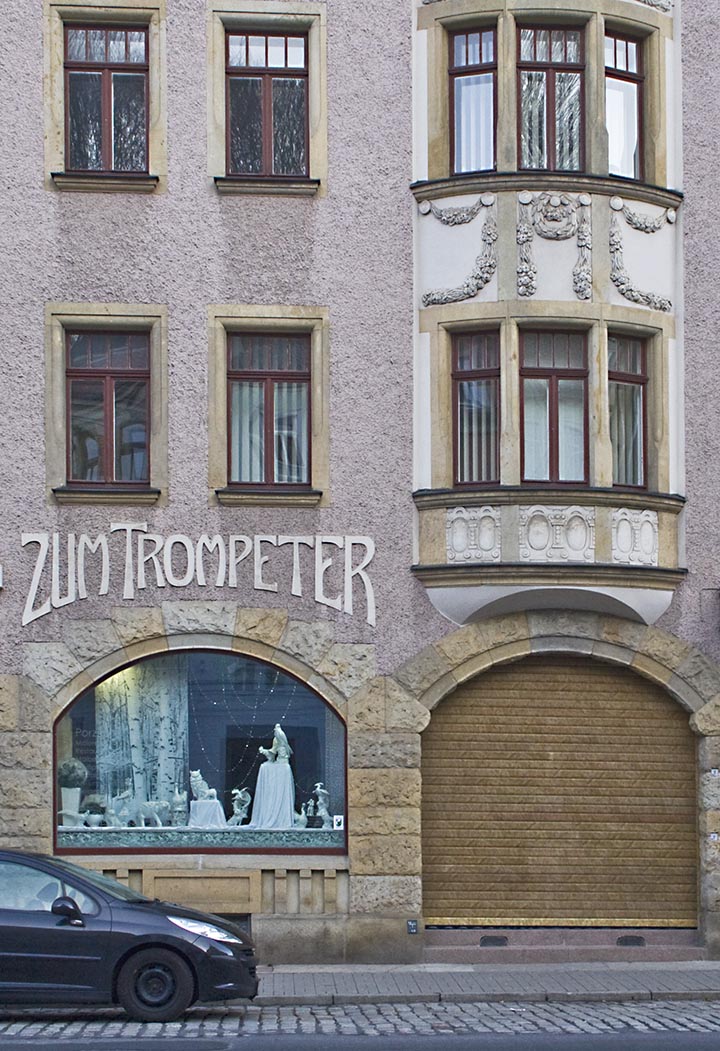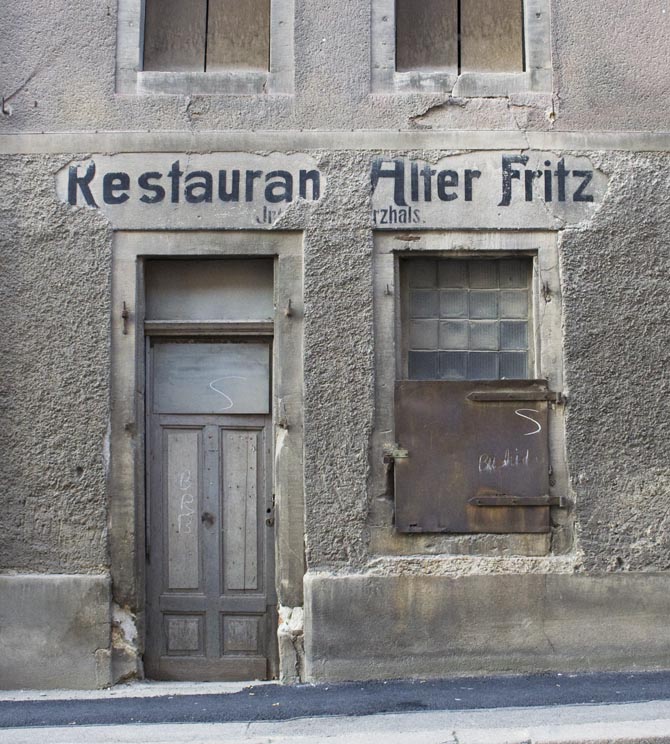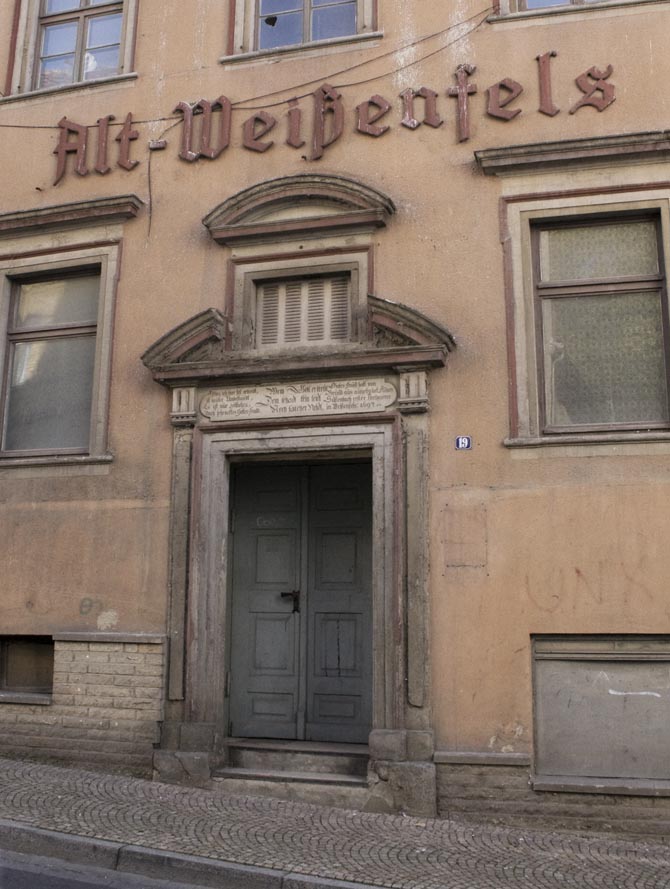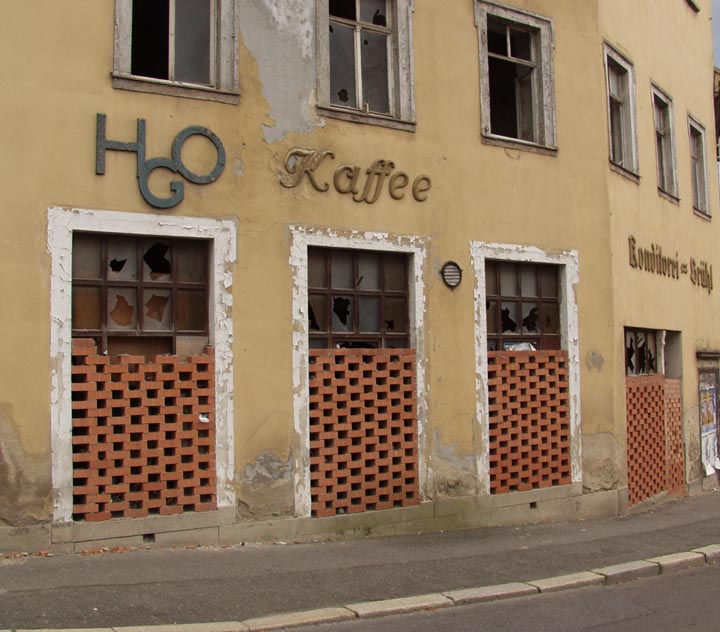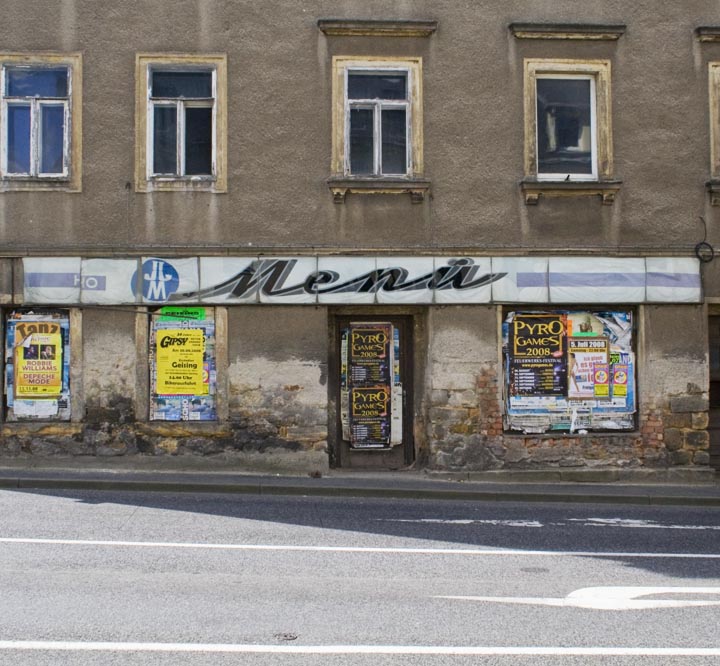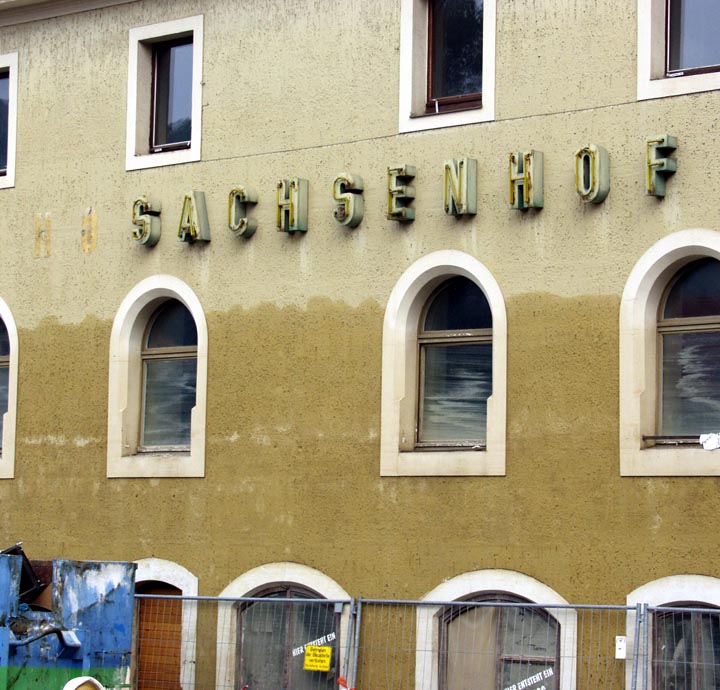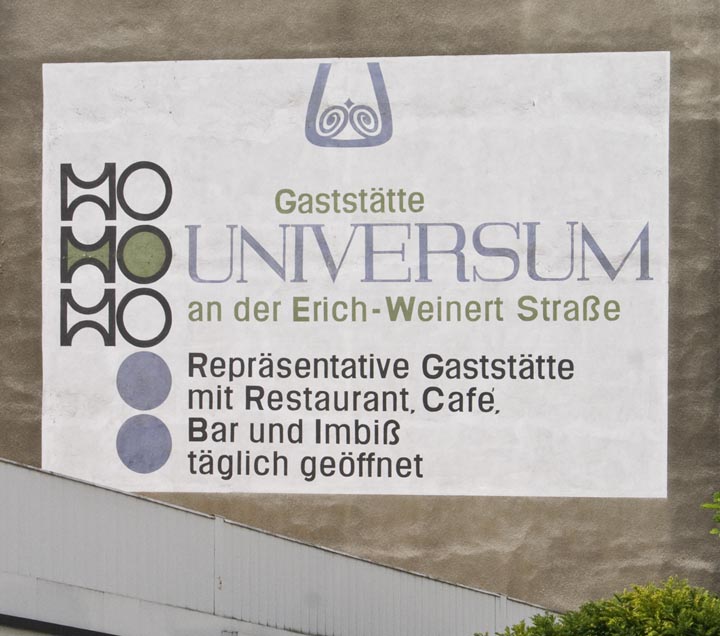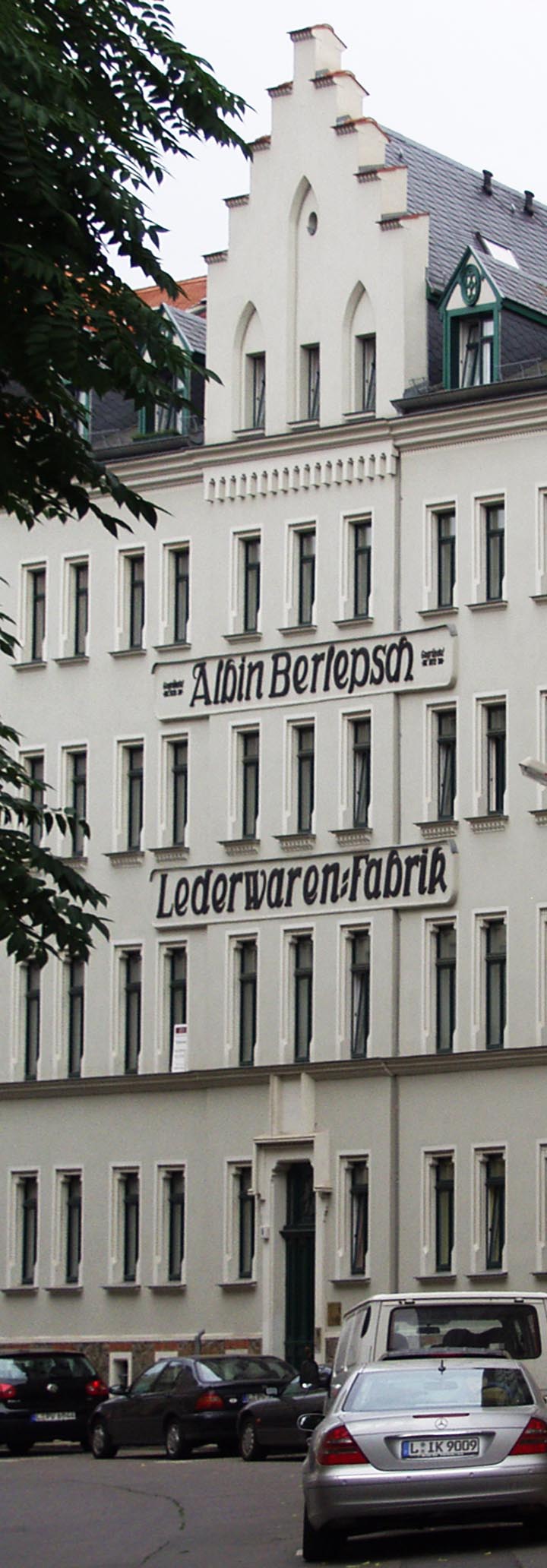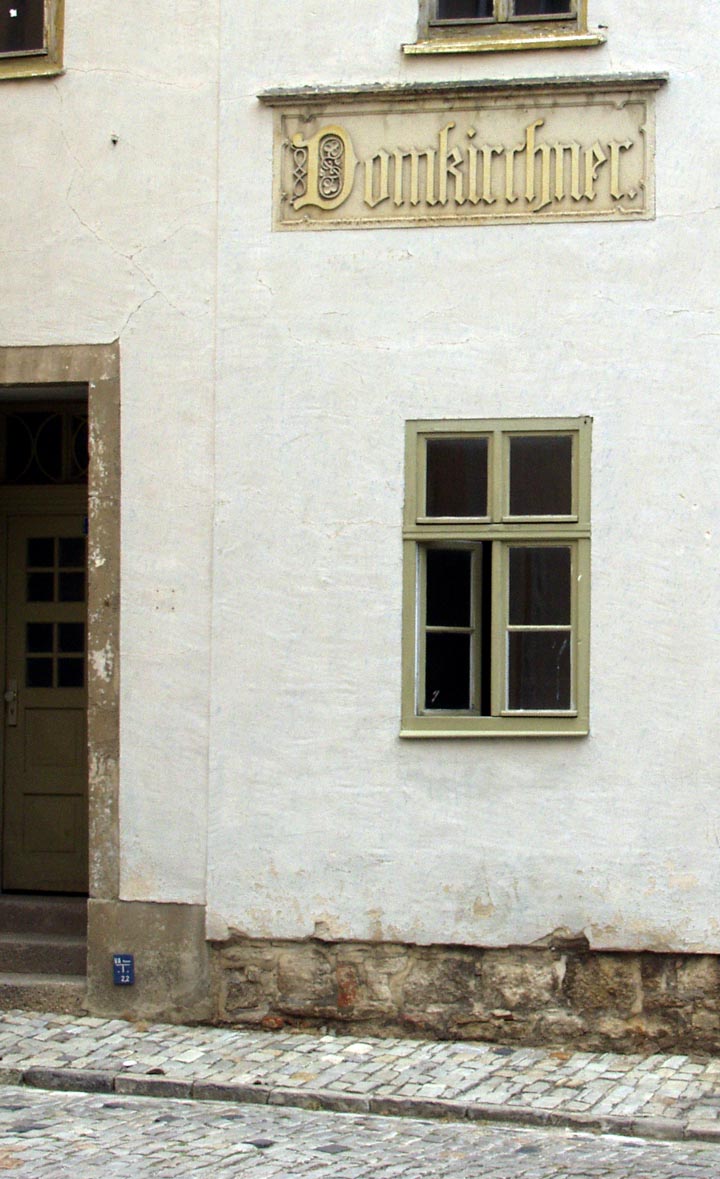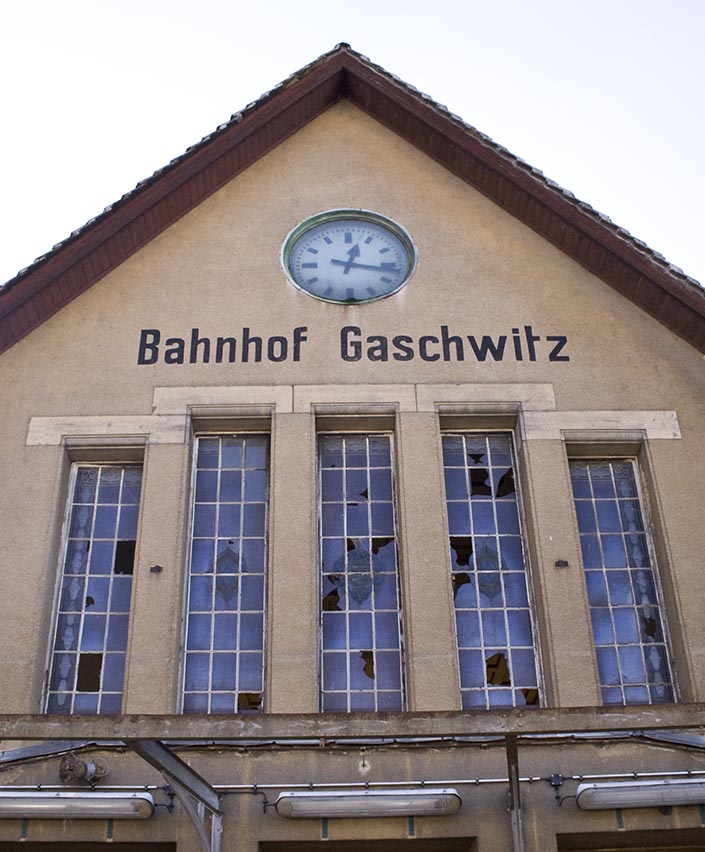
Façadenschriften
(Wahrscheinlich) aus Geyer:
Fleisch & Wurstgeschäft Robert Krausse
Typographisch gibt es hier natürlich einiges zu mäkeln — das fehlende Divis, die fehlenden Abstände, die oben eingespart wurden, um dann offensichtlich unten verwendet zu werden, um ein riesiges Loch in den Namen zu reißen …
Dafür sind die ch-Ligaturen witzig und alle Fehler haben den Charme nicht zerstören können, den das Ding insgesamt verströmt.
aus Naumburg:
Geschlampt wurde auch früher schon kräftig, besonders bei der Interpunktion. Typographisch ohnehin nicht der große Wurf — Papier u Schreibwaren Otto Blaubach.
aus Gotha:
Louis Ebert jun. Weinhandlung · Likörfabrik
Die restlichen drei sind aus Weißenfels:
… und schon wieder ein fehlendes Divis. Manchmal habe ich fast den Eindruck, daß die Façadenschriften nach Buchstabenzahl abgerechnet werden und mancher Auftraggeber deshalb die Interpunktion spart: Mohren Apotheke
Alt-Weißenfels
Was ich hier feſt gebaut,
iſt lauter Unbeſtandt,
Es iſt nur Zeitliches,
doch ſchencktes Gottes Hand.
Wem Gott erfreut
Dem ſchadt kein Leidt
Noch falcher Neidt
Dieſes Haus hatt von
Grund aus aufgebauet: Adam
Süßenbach erster Paruguirer
in Weißenfels: 1697
Handgestrickt, disproportioniert, aber irgendwie doch charmant: Restaurant Alter Fritz
Die HO (Handelsorganisation) war ein staatlicher Handelsbetrieb in der SBZ und DDR. Gegründet wurde die HO 1948, um nach dem Krieg in der SBZ (Sowjetische Besatzungszone) erstmals freie Waren zu verkaufen, also solche, die ohne Lebensmittelmarken oder Bezugsscheine erworben werden konnten — wenn auch zu deutlich höheren Preisen. Mit dem Auslaufen der Lebensmittelmarken entwickelte sich die HO zu einer regulären, wenn auch stark dominanten staatlichen Handelskette, die aus dem Erscheinungsbild der DDR nicht wegzudenken war und schließlich Einzelhandelsgeschäfte verschiedener Sparten, Warenhäuser, Gaststätten und Hotels betrieb.
Nachfolgend Façadengestaltungen von HO-Gaststätten.
in Zeitz:
im Erzgebirge:
in Königstein:
möglicherweise in Lychen:
in Guben:
Da die HO-Gastronomie nicht gerade für überschäumende Creativität und guten Kundendienst (»Bitte warten, Sie werden plaziert!«) bekannt war, könnte man bei der vorstehenden Abbildung lakonisch die Einheit von Inhalt und Form attestieren: Grausige Typographie als angemessene Präsentation der DDR-Gastronomie. Da es sich hier aber offensichtlich um eine restaurierte (womöglich gar denkmalgeschützte) Beschriftung handelt, kann ich auch nicht völlig ausschließen, daß der Schaden erst bei der Restauratin entstanden ist.
Hier das nächste halbe Dutzend:
aus Naumburg, schlecht ausgeglichen, aber trotzdem schön: Domkirchner. — mit Punkt natürlich
aus Bamberg ein trauriger Beleg für den Niedergang von gewerblicher Werbung: ehemals Fränkische Weinstube, jetzt Dönerschmiede und Fahrschule
aus Leipzig liebevoll saniert: Albin Berlepsch · Lederwarenfabrik
aus Wernesgrün: Vereinigung volkseigener Betriebe „Trikot“ · Wernesgrüner Wirkwarenfabrik
aus Riesa: ZUM GROSSEN CHRISTOPH, der dringend ein ebensolches ẞ bräuchte
einerseits sehr schön, andererseits recht steril und zu offensichtlich auf heile Touristenwelt getrimmt — Stein am Rhein: Joh. Etzweiler. Spengler.
Radio Borsdorf Meißen:
Ferd. Thürmer, Hof-Pianofortefabrik. Meißen:
Bäckerei H. Adam Meißen:
Zum Trompeter Meißen:
… und dreimal Bahnhof Gaschwitz:
Façadenschriften